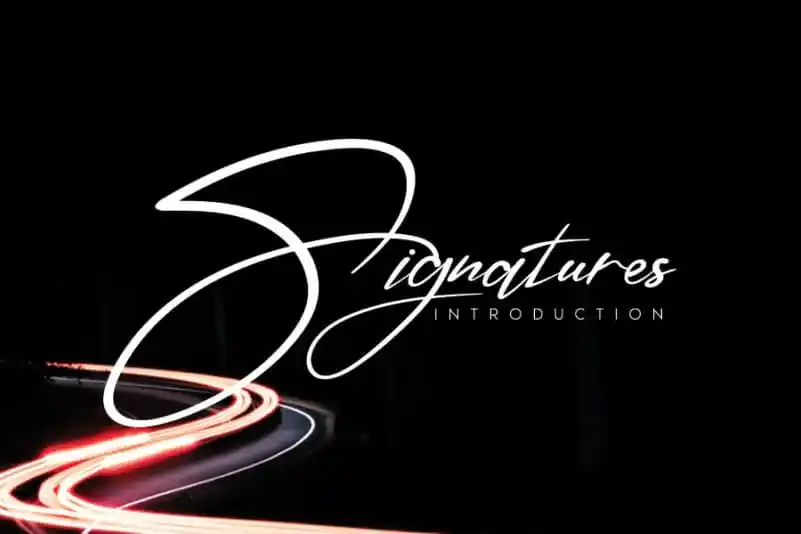
Signatures Handwritten Font – Download Grátis
A fonte ‘Signatures Handwritten Font’ é uma combinação única de elegância sofisticada e autêntica calligrafia. Este tipo de letra clássico mantém um ar descontraído, tornando-a perfeita para criar designs únicos e impressionantes. Ideal para aqueles que buscam uma fonte de escrita manuscrita com profundidade e estilo duradouros, esta é uma opção irresistível para projetos digitais. É a fonte certa para quem valoriza a arte da escrita e busca trazer personalidade ao seu trabalho. Através dela, você pode alcançar um equilíbrio entre elegância e conforto no design.